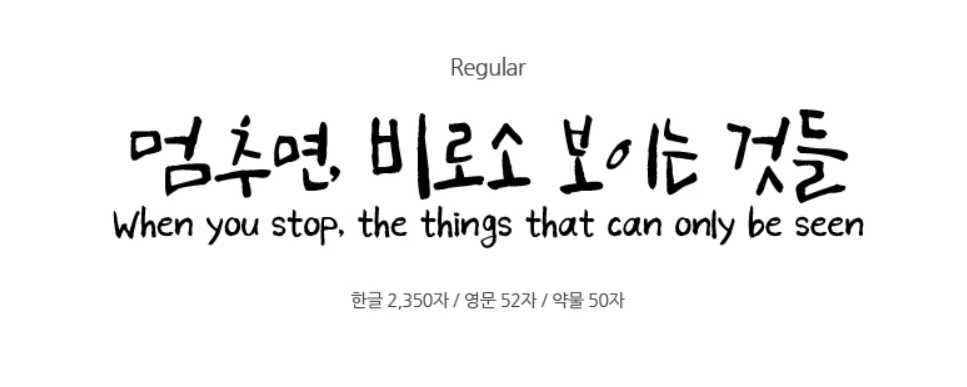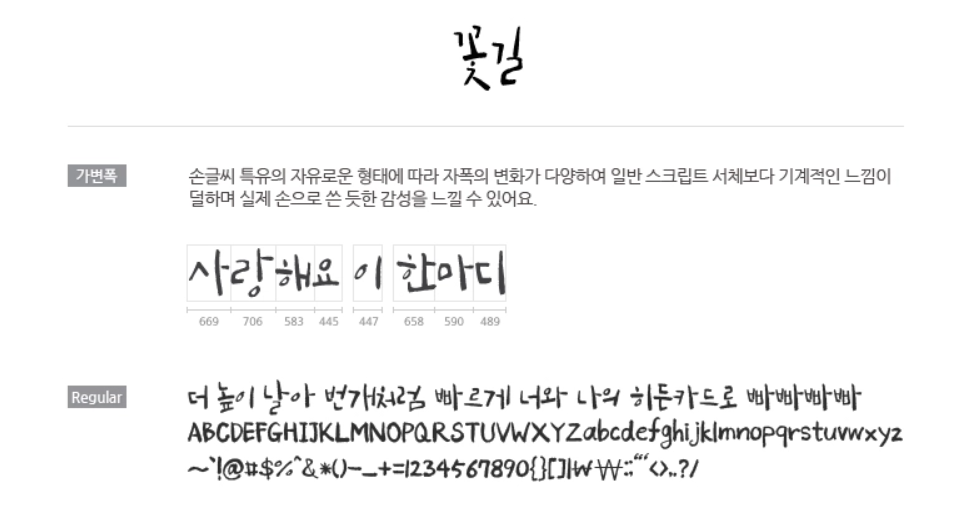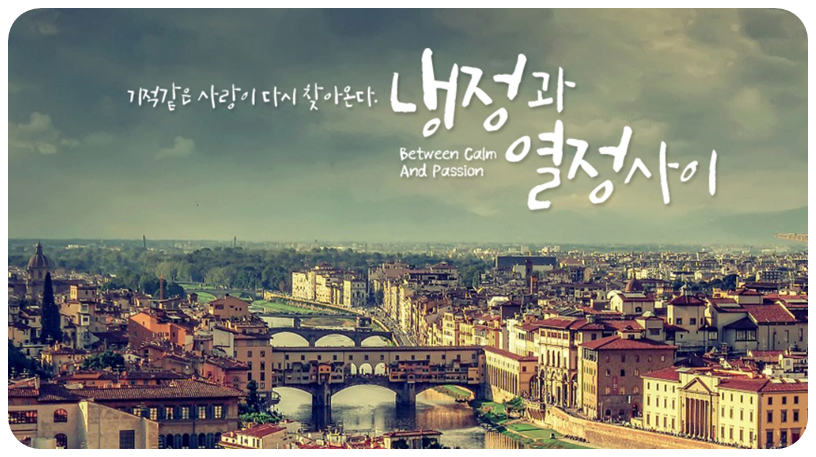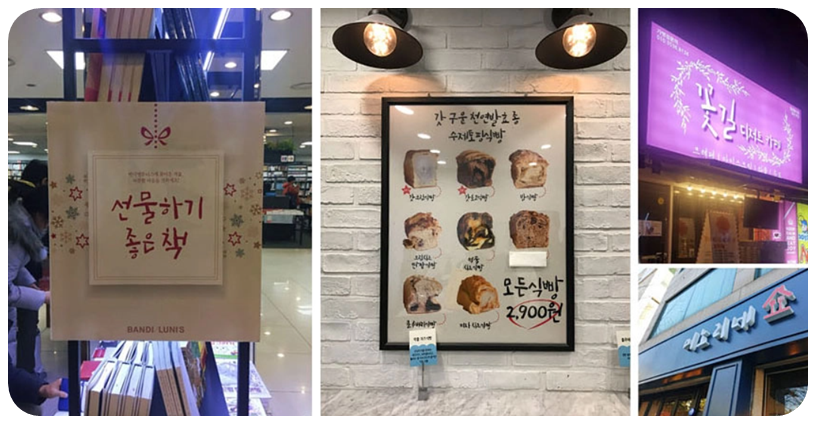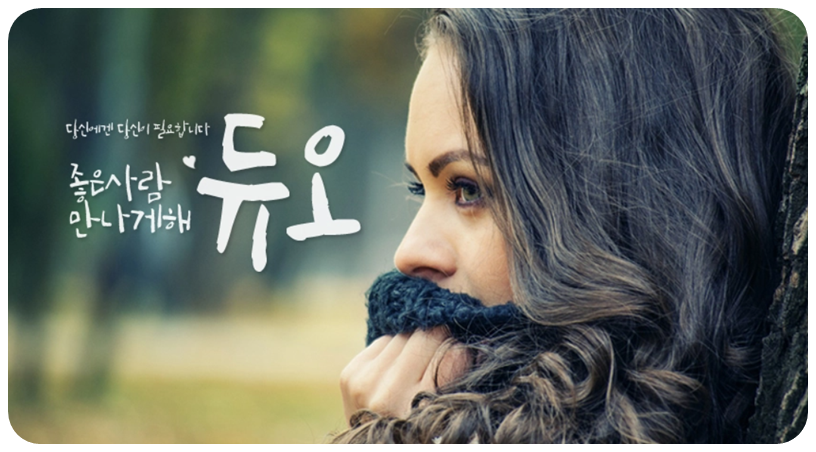
감성적인 캘리그라피 폰트를 찾고 있다면, 이 폰트는 놓치면 아쉽습니다.
붓글씨 특유의 자연스러운 흐름과 따뜻한 분위기를 담은 ‘상상토끼 꽃길’ 폰트를 소개합니다.
상상토끼 꽃길 폰트란?
‘꽃길’ 폰트는 캘리그래퍼 상상토끼 용이 작가의 붓글씨를 기반으로 제작된 감성 서체입니다.
자연스럽고 부드러운 필체가 특징이며, 따뜻한 감성을 전달하는 데 최적화된 디자인 폰트입니다.
폰트 특징
✔️ 붓글씨 기반 캘리그래피 서체
✔️ 자연스럽고 감성적인 필기체 스타일
✔️ 로고, 간판, 썸네일 디자인에 최적
특히 브랜드 로고나 감성 콘텐츠 제작 시, 별도의 디자인 없이도 분위기를 살릴 수 있는 것이 큰 장점입니다.
폰트 구성 정보
| 항목 | 내용 |
|---|---|
| 서체명 | 꽃길 Regular |
| 한글 | 2,350자 |
| 영문 | 52자 |
| 기호 | 약 50자 |
활용 추천
📌 카페/매장 로고 디자인
📌 SNS 카드뉴스 및 썸네일
📌 감성 브랜딩 디자인
📌 유튜브 썸네일 및 포스터
실제 사용자 후기에서도 로고 제작, 간판 디자인 등에서 높은 만족도를 보이고 있습니다.
Q4. 어떤 디자인에 잘 어울리나요?
감성 콘텐츠, 카페 로고, SNS 디자인, 브랜드 이미지 제작 등에 잘 어울립니다.
마무리
상상토끼 꽃길 폰트는 감성적인 붓글씨 스타일을 그대로 담아낸 매력적인 무료 서체입니다.